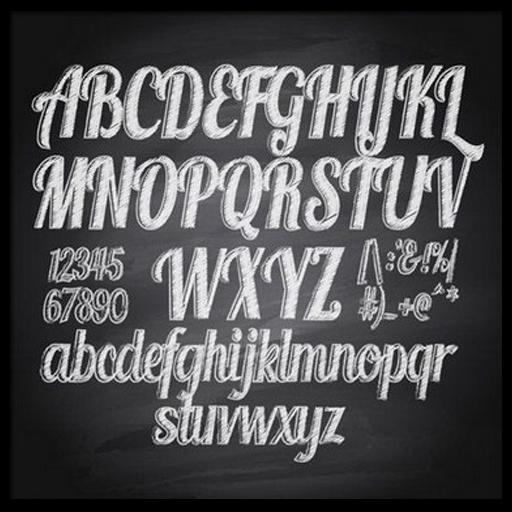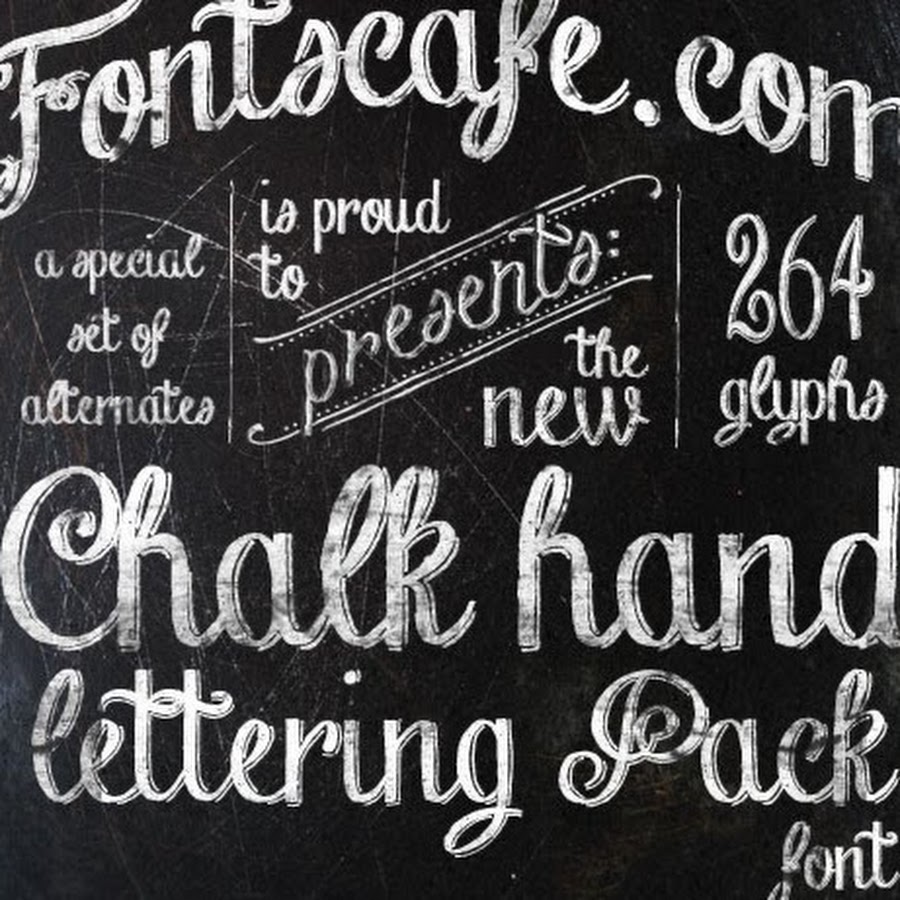
50+ лучших шрифтов мелом для фотошопа (+кириллица)
В данной статье сможете бесплатно скачать шрифты мела для фотошопа, которые пригодятся вам в разных дизайнерских решениях на сайтах, иллюстрациях, приложениях или даже в офлайне (например, иногда владельцы кафе оформляют меню в этом стиле). Подобный вариант с декоративным шрифтом надписи мелом также неплохо будет смотреться в полиграфии. Где бы вы его не применили, подборка ниже окажется полезной. Всего собрали около 50-ти объектов на любой вкус.
Перед тем, как перейти к рассмотрению материалов, хочется заметить, что некоторые из них изначально (в превью) могут не вызывать ощущения шрифта мела на доске. Однако если вы в качестве фона добавите подходящую текстуру, то имитацию надписи, практически невозможно будет отличить от настоящей.
Как видите, вариантов реализации текста великое множество, в частности вы смело можете использовать разные цвета для него, не обязательно белый. По стилистике решения тоже слегка отличаются — есть рукописные, жирные, строчные, заштрихованные буквы и т.
DK Crayon Crumble
Rayando
FFF Tusj
Syphon Spritz
Grutch Shaded
pencilPete
Hesster Moffett
Eraser
Chalk Line
Conte Script
PWDolphins
vtks noise
Colored Crayons
Coffee House
Denne Milk TeaИспользуйте эти фонты для создания различных стилизованных текстов. Они пригодятся для оформления сайтов, праздничных надписей, открыток, баннеров или плакатов.
Все зависит от воплощения ваших творческих фантазий.
Black Crayon
DJ Gross
[ank]*
PWScritch
Orange Juice
Vtks Love Love
Vintage One
WC RoughTrad Bta
Return To Sender
School Book New
Villa Didot
Tequilla Sunrise
Chalk Hand Lettering Shaded
Universal College draft
Sketch
Monster Unleashed
Smudgie Crayon
Sketch Serif
Angeline Vintage
Chalkboard by Marta van Eck
KG Second Chances
KG Ten Thousand Reasons
Appleberry
Firestarter Z
KG Broken Vessels Sketch
PWChalk
MrsKate
Film Cryptic
Lost In The Sound
DK Keswick
Кстати, многие из текущих шрифтов мелом на доске перекликаются с другими подборками для фотошопа. Например, достаточно часто встречаются так называемые Sketchy шрифты с широкими заштрихованными буквами, хватает и рукописных вариантов. Как только вы добавляете соответствующий фон зеленой или черной доски, а символам задаете белый цвет — тексты сразу вызывают нужные ощущения. Теоретически, для бэкграунда можно еще попробовать разные темные текстуры, возможно, металлические или гранжевые.
Русские шрифты мелом на доске
Традиционно с кириллицей дела обстоят не лучшим образом — по сравнению с обычными латинским вариантами данных материалов в разы меньше. Удалось найти всего две официальных ссылки где можно бесплатно скачать русский шрифт мелом для фотошопа. Если вы знаете больше, присылайте в комментариях.
LC Chalk
Schist
Опять же, если взять текстуру школьной доски и добавить один из трех вариантов ниже, то получите плюс-минус похожую по стилистике картинку.
Capture it
CrashCTT
Boyarsky Normal
Теоретически, можно также попробовать взять русские жирные шрифты и применить к ним определенные эффекты: немного потертости, наложить какую-то винтажную текстурку и т.п. Альтернативный вариант — платные русские шрифты мелом с кириллицей, например.
Vector HandDrawn Cyrillic Alphabet
Collection Sketchy Alphabets
Halloween Chalk
Back School Chalk Text
ChalkA Alphabet Title Big
Итого. получилось найти чуть больше 50-ти шрифтов надписи мелом на доске. Их в сети, разумеется, гораздо больше — можете просмотреть сайты-архивы по типу Dafont, 1001fonts, Fontspace и другие. Ищите по ключевику «chalk font». Присылайте интересные варианты в комментариях.
Как сымитировать надпись мелом в фотошопе
Для оформления свадьбы потребовалась имитация доски с написанным мелом текстом. Эта доска стоит позади столика со сладостями и довольно большая. Вот образец того, на что нужно было ориентироваться. Первый шаг – погуглить. Из первого десятка результатов я выбрала два: результаты показались мне похожими на правду.
Пепел
Ashes — один из совершенно бесплатных шрифтов для классной доски, созданный IceDragon в 2015 году. Обратите внимание на уникальный шрифт, который поможет вам создать неповторимый дизайн.
Безымянный шрифт
Шрифт Nameless, разработанный Анной Иванир, — один из новых рисованных шрифтов для классной доски, в котором есть разные символы и множество дополнительных функций.Шрифт поддерживает международные языки, включает буквы верхнего и нижнего регистра, а также знаки препинания и цифры.
ЩЕТКА